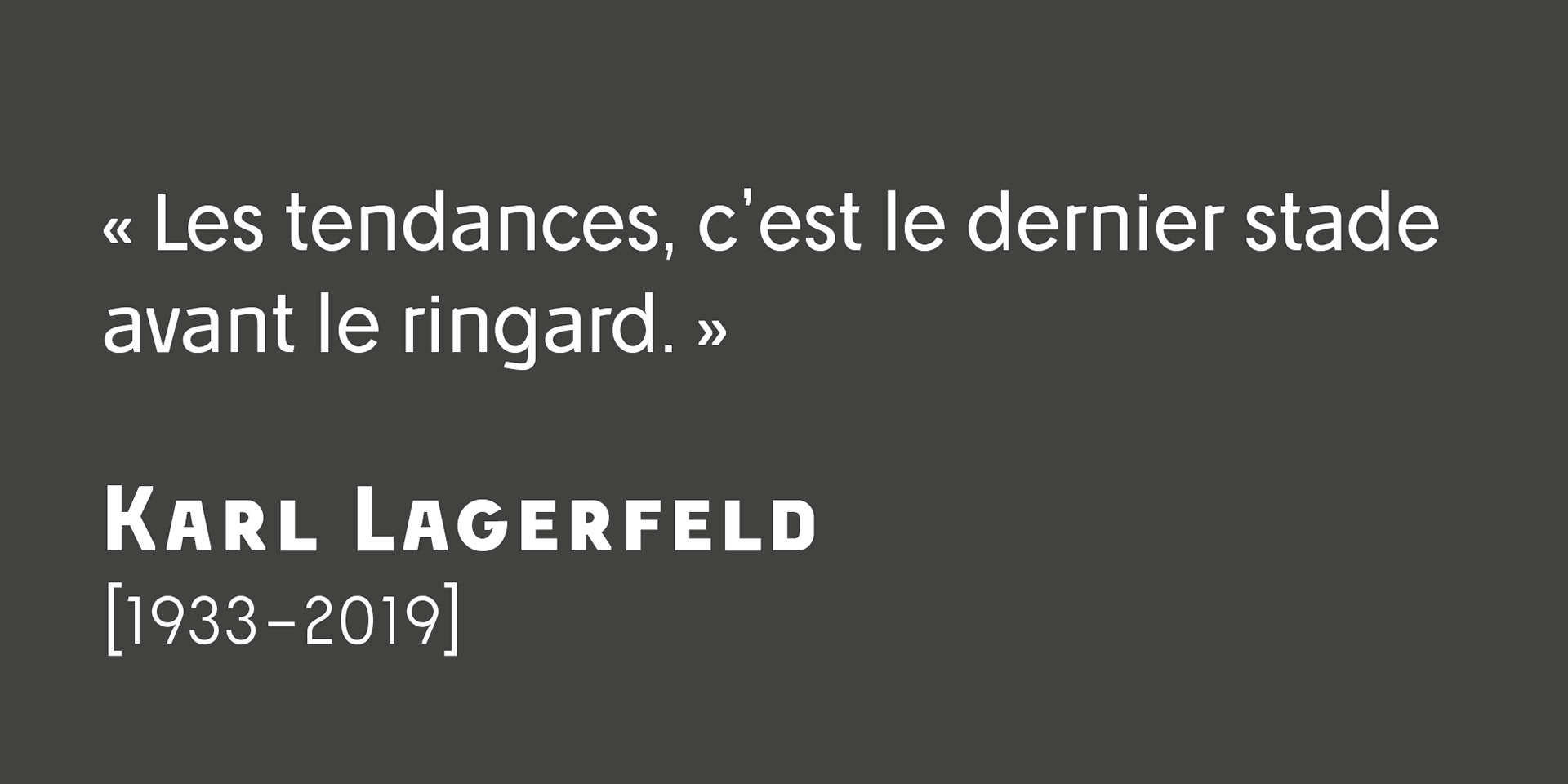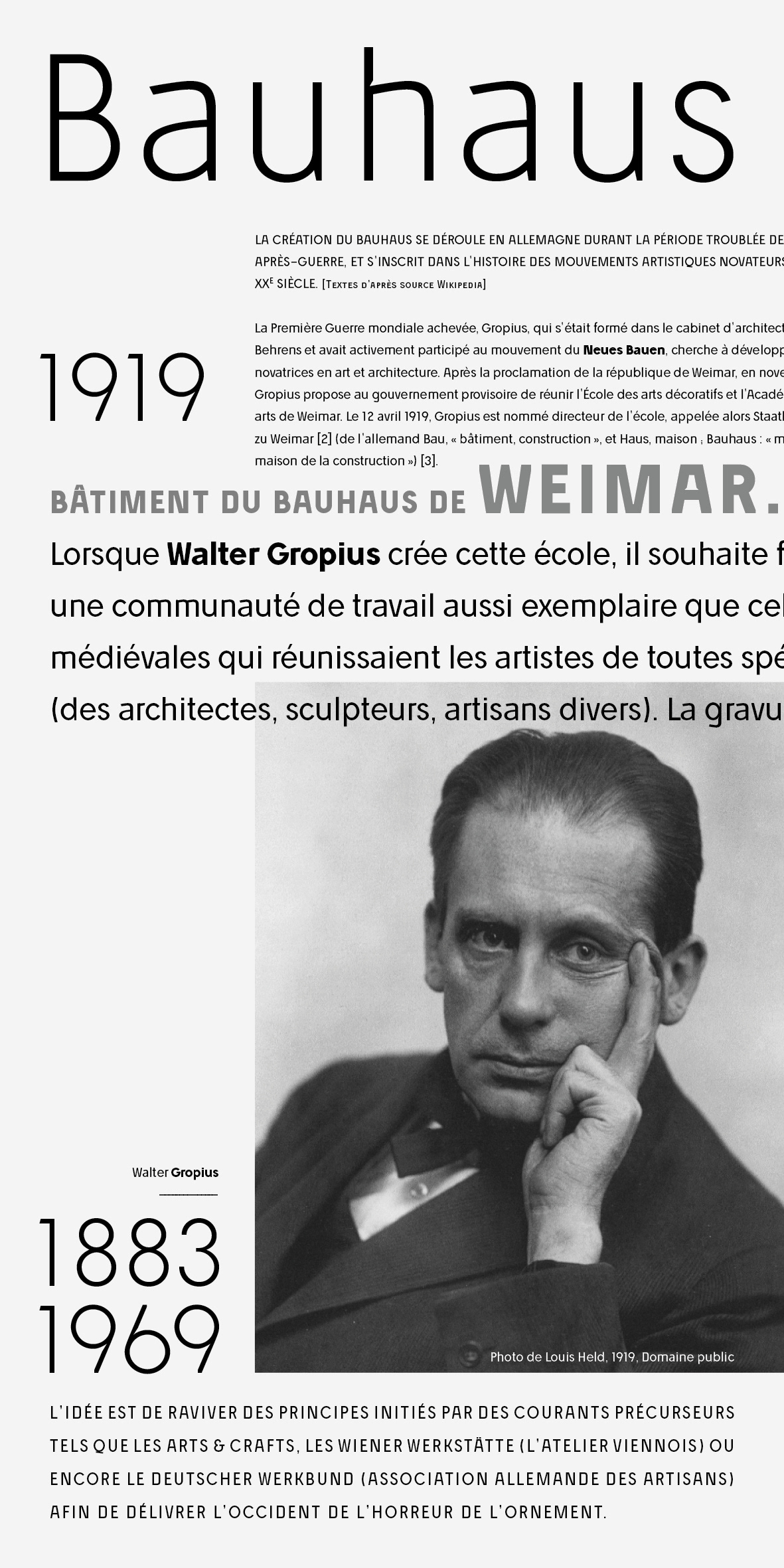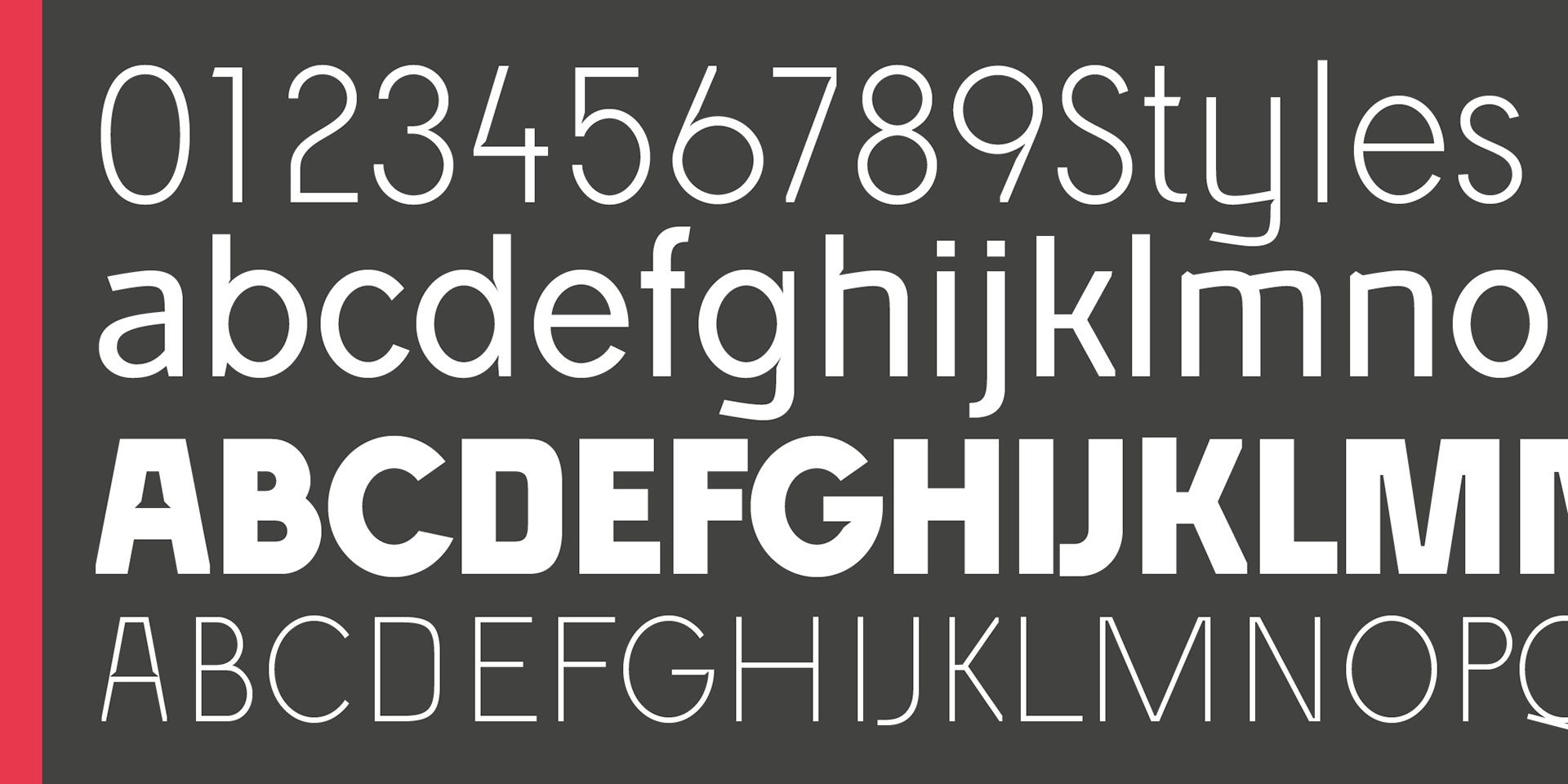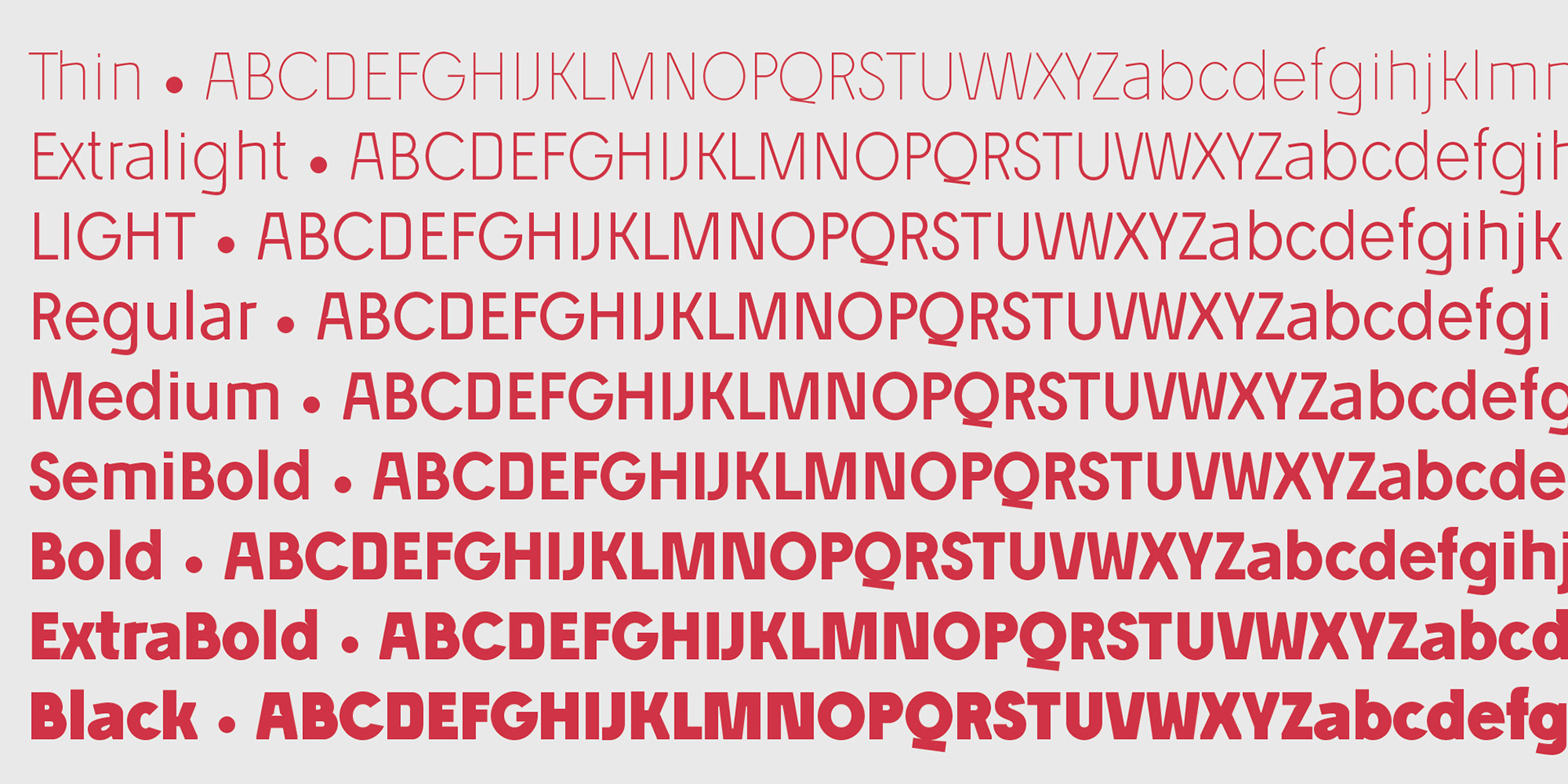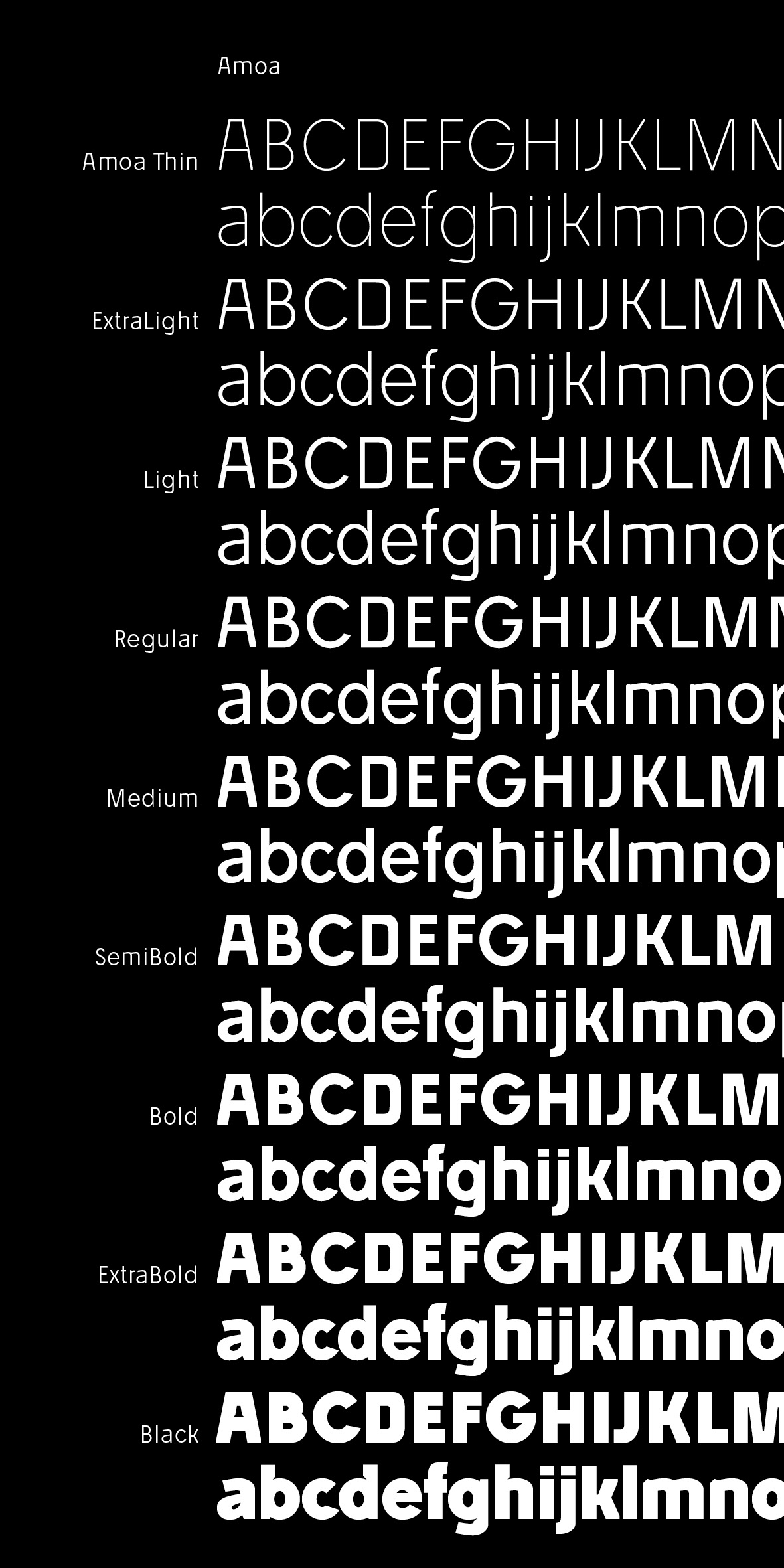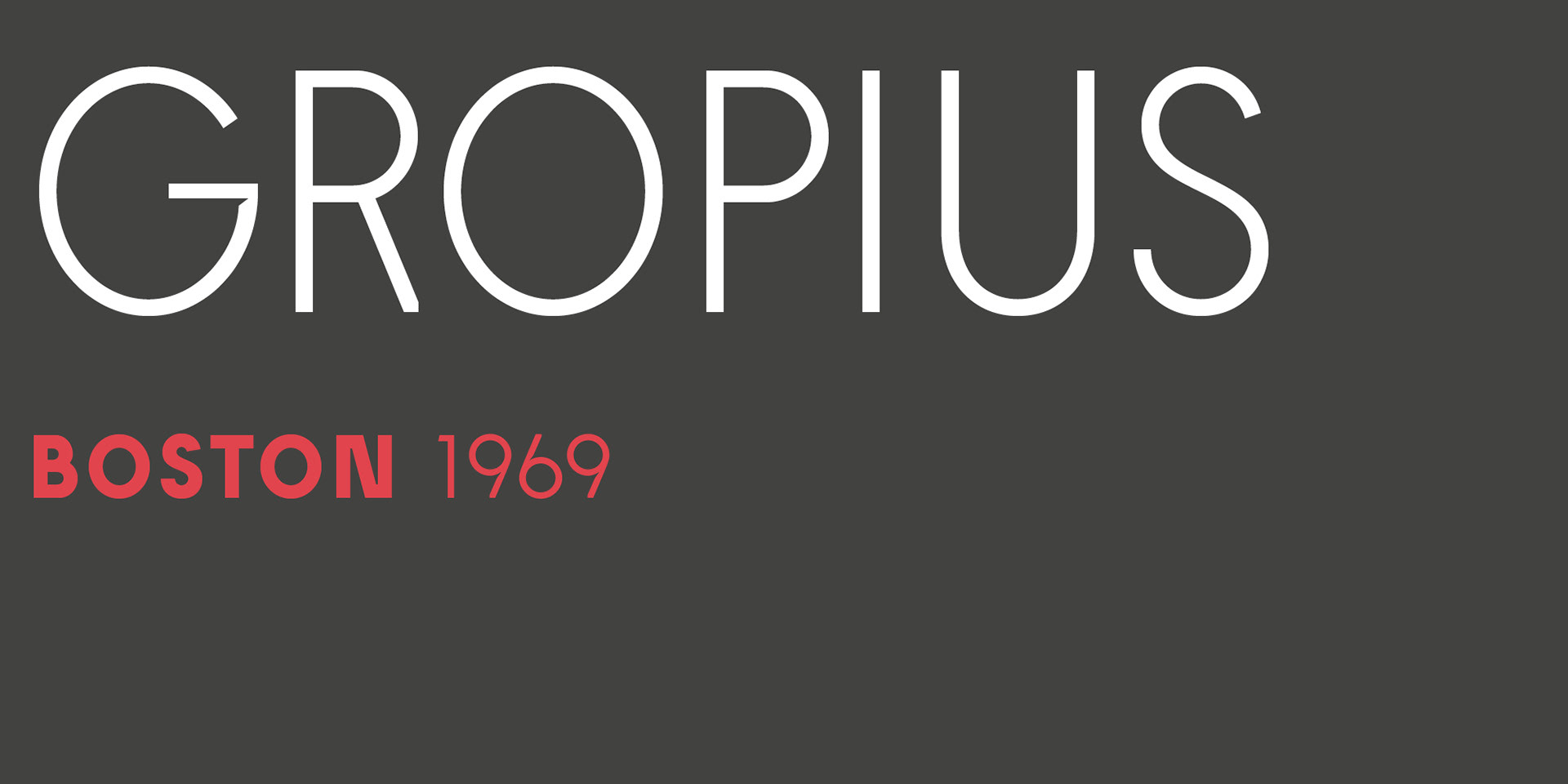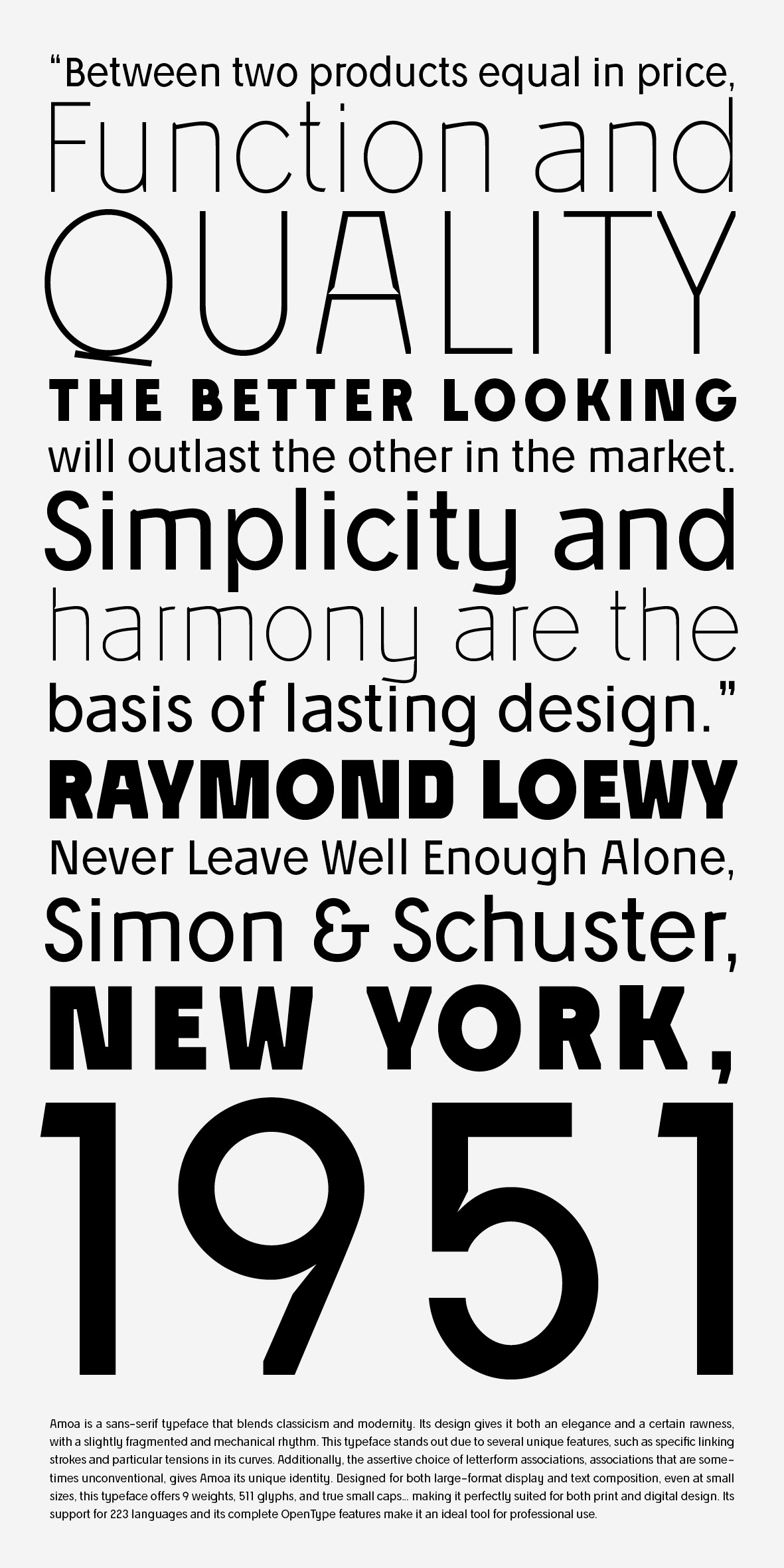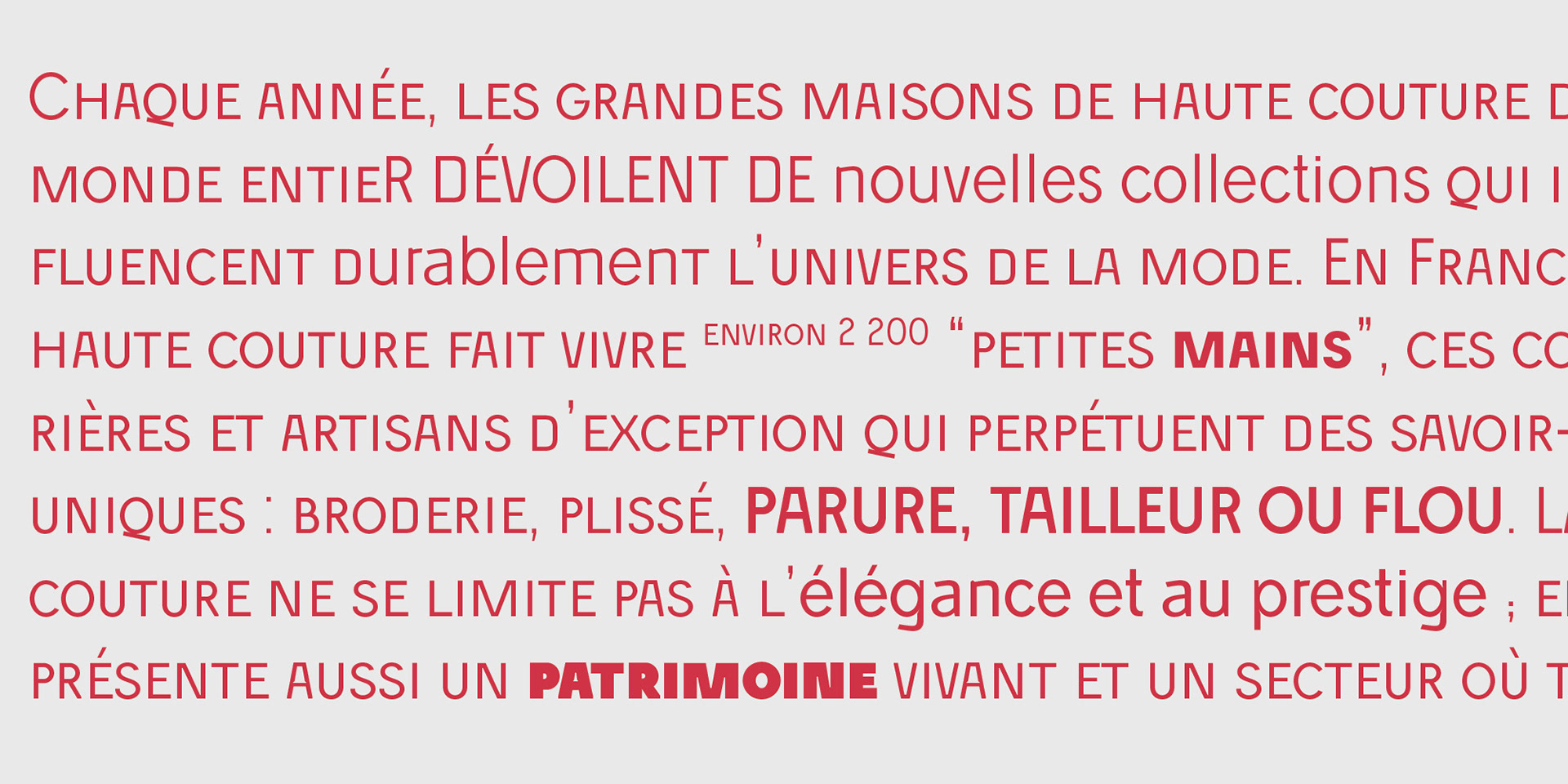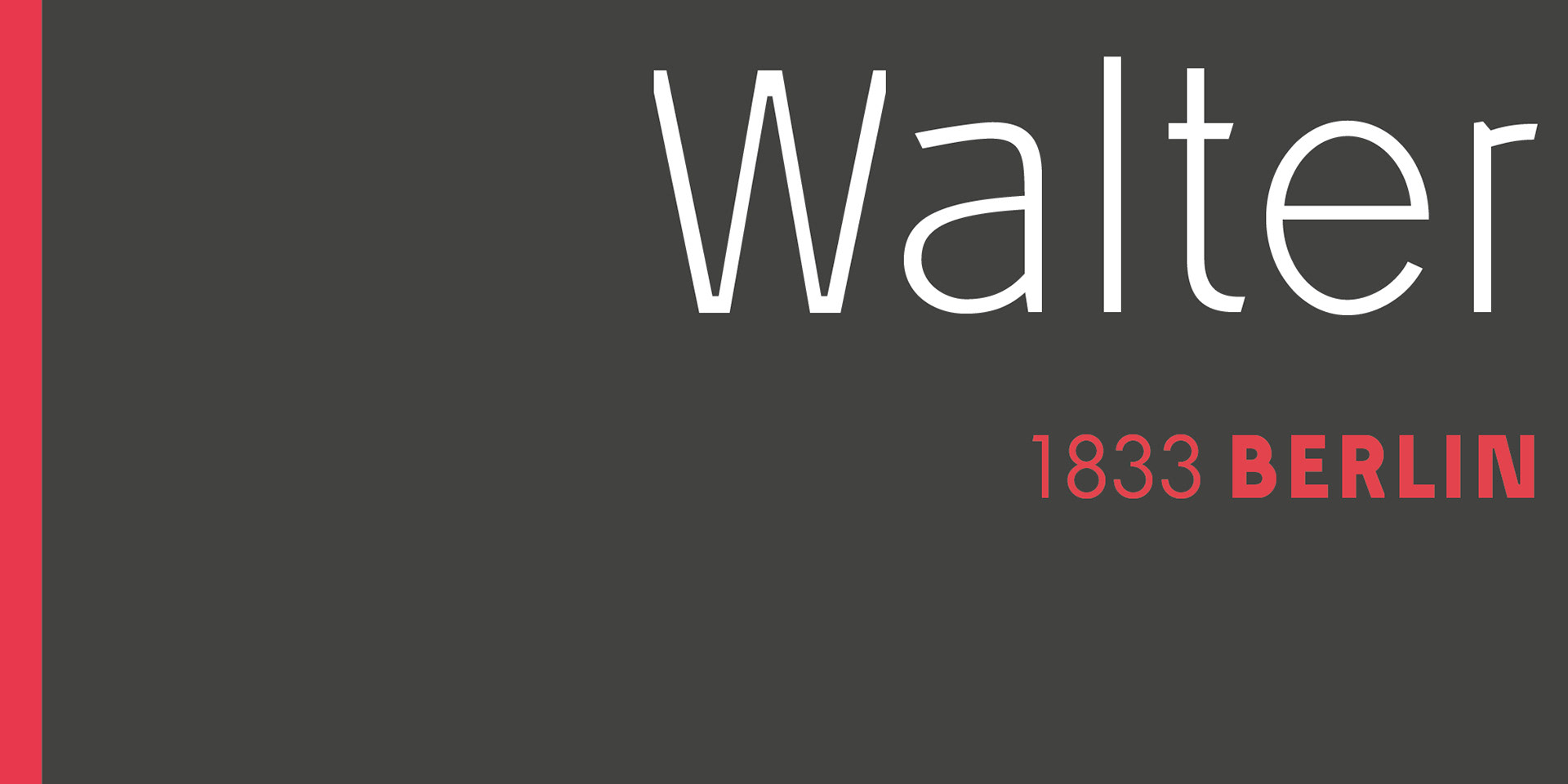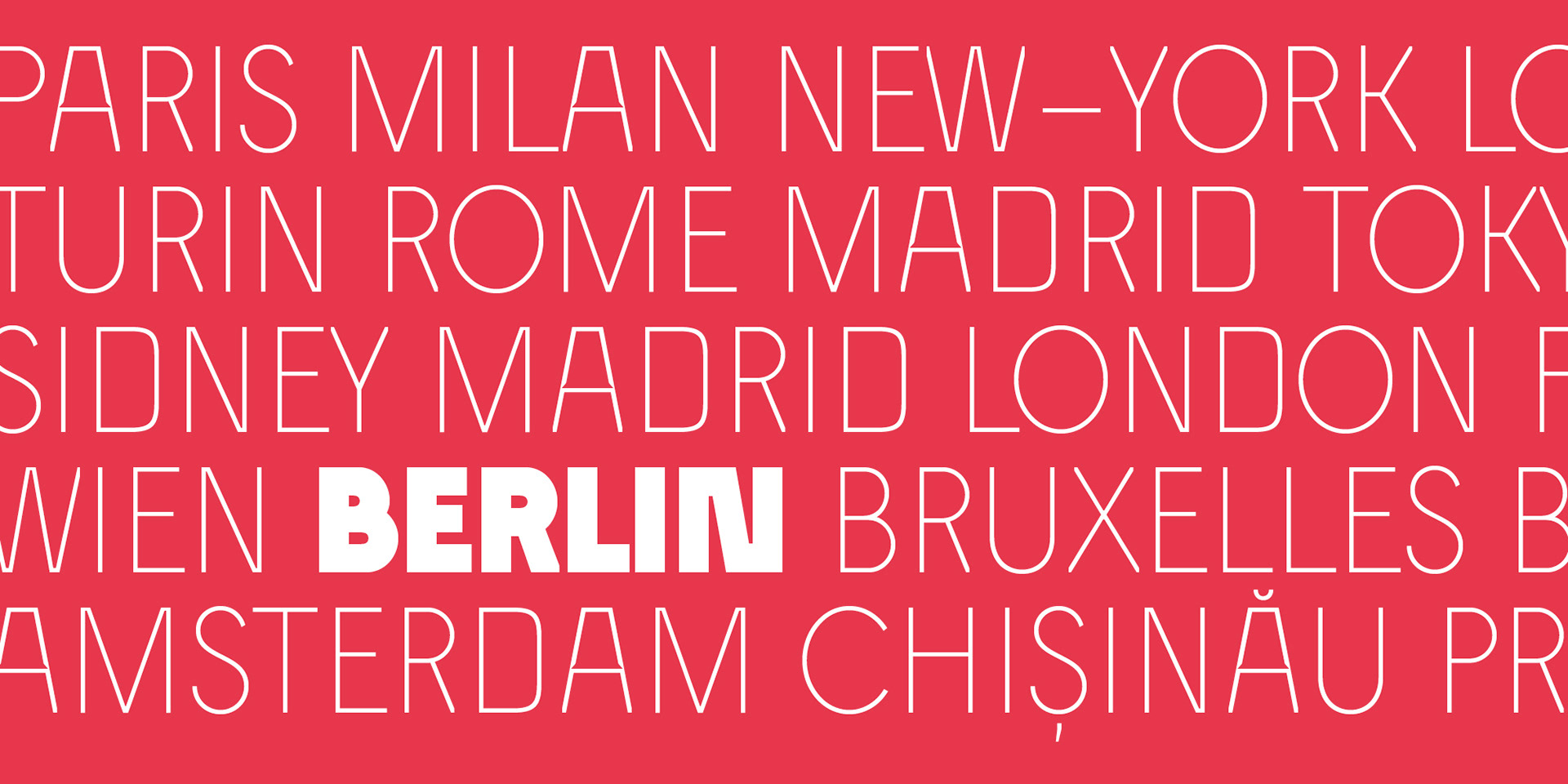
9 fontes (styles), prêtes à l’emploi pour au moins 223 langues utilisant l'alphabet latin.
AmOA
AmOA is a SANS serif TYPEFACE - designed by Loïc Choquet.
Amoa is designed for both large-format display and text composition. Even at small sizes, this typeface offers 9 weights, 511 glyphs, and true small caps, making it perfectly suited for both print and digital design. Its support for 223 languages and its complete OpenType features make it an ideal tool for professional use, on Mac or PC.
Amoa est un caractère conçu tant pour le titrage que pour la composition de textes, même en petits corps. Cette police propose 9 graisses, 511 glyphes par fonte, de véritables petites capitales… ce qui la rend parfaitement adaptée aux travaux d'édition. Amoa fonctionne aussi bien pour le design imprimé que numérique.
Elle est utilisable pour des compositions de texte en 223 langues différentes (cf. liste plus bas), et ses fonctionnalités OpenType complètes en font un outil idéal pour un usage professionnel sur Mac ou PC.
Amoa, an exquisite sans-serif typeface that unites the elegance of classic forms with the boldness of modern aesthetics. Amoa is a sans-serif typeface that blends classicism and modernity. Its design gives it both an elegance and a certain rawness, with a slightly fragmented and mechanical rhythm. This typeface stands out due to several unique features, such as specific linking strokes and particular tensions in its curves. Additionally, the assertive choice of letterform associations, associations that are sometimes unconventional, gives Amoa its unique identity.
Amoa est une police linéale qui allie classicisme et modernité. Son design lui confère à la fois élégance et une certaine rudesse, avec un rythme légèrement fragmenté et mécanique. Cette police se distingue par plusieurs caractéristiques uniques, telles que des déliés de liaison spécifiques et des tensions particulières dans ses courbes. De plus, le choix affirmé des associations de lettres, parfois non conventionnelles, donne à Amoa son identité unique.